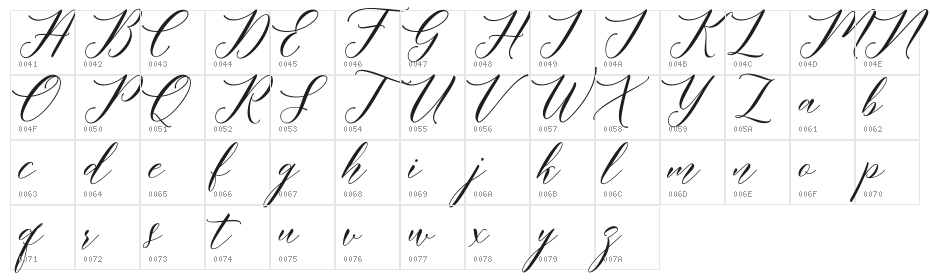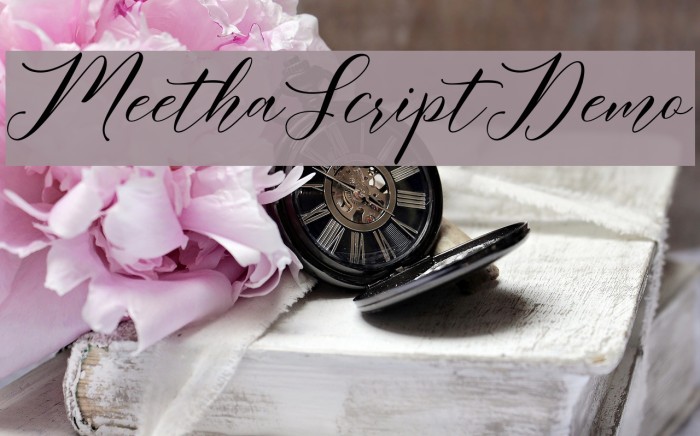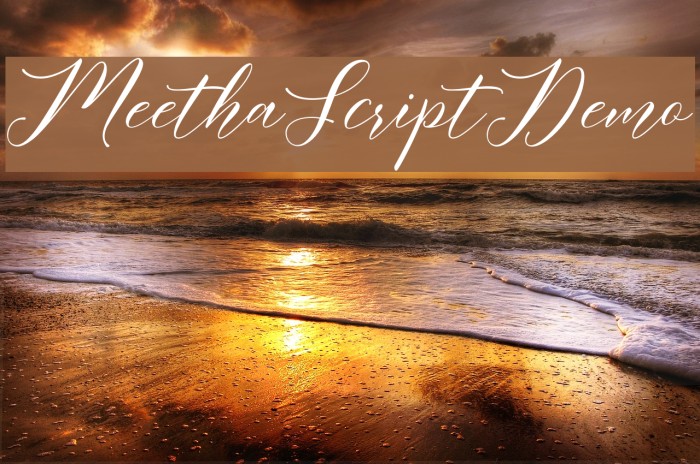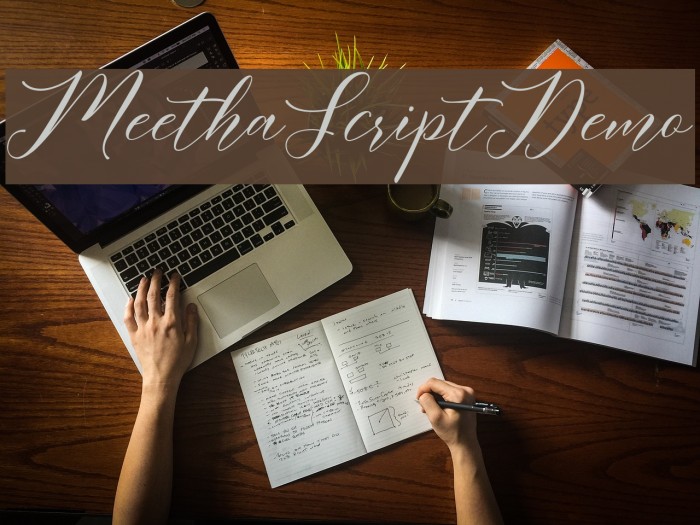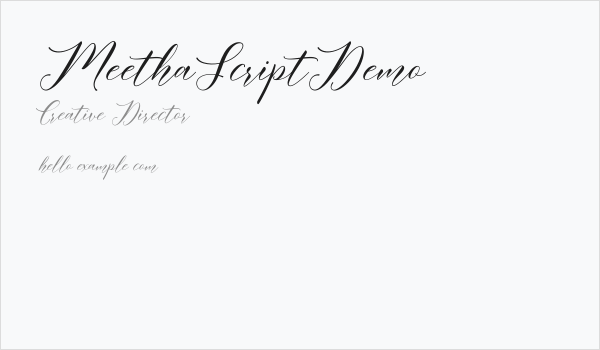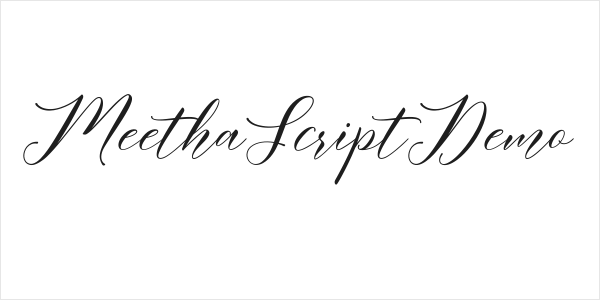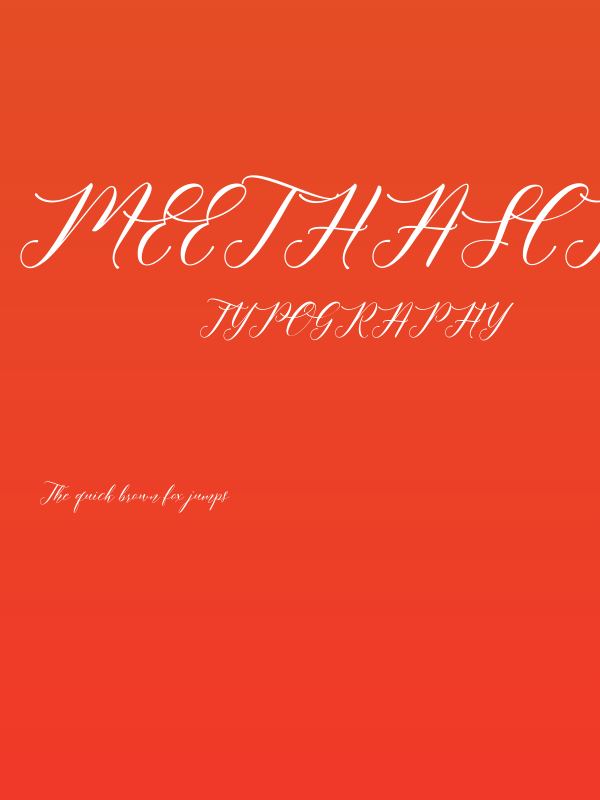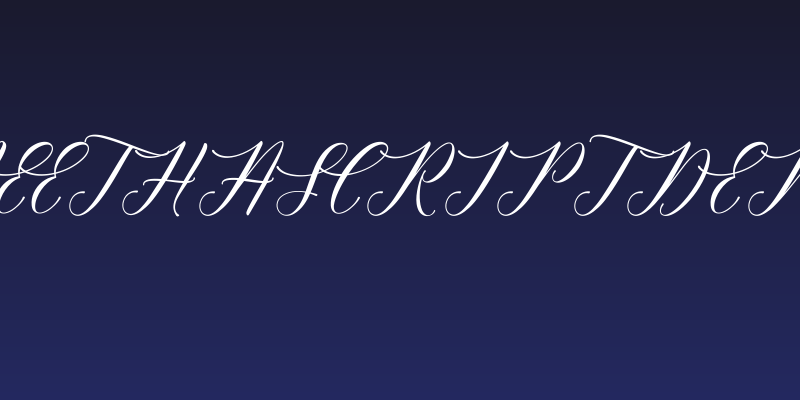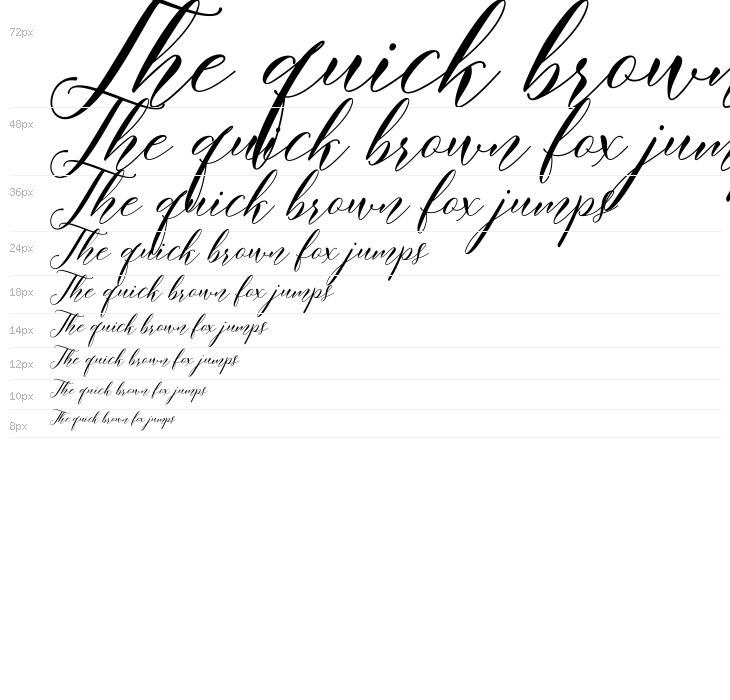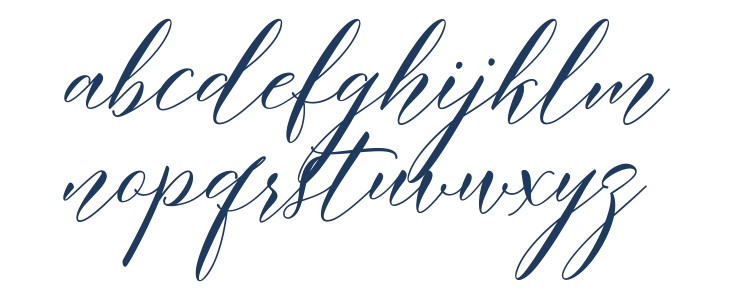
MeethaScriptDemo Font
✎ Calligraphic
| Gesamtstil | Elegant, Calligraphic |
| Anwendungsfall | Headlines, Invitations, Branding |
| Vorgeschlagene Projekte | Ideal for wedding invitations, elegant branding, greeting cards, and luxury product packaging. |